Kisah Sans Serif, Font Populer Dunia yang Dulu Dicaci
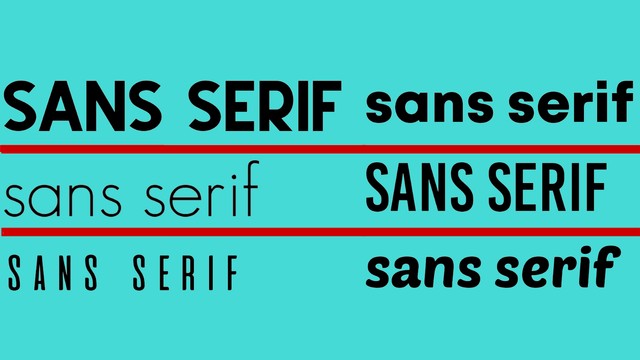
Sans Serif telah menjelma sebagai standar font dunia. Yang terbaru, Gojek mengubah font-nya menjadi Sans Serif. Menyusul Google, Spotify, Netflix, hingga Pinterest yang sudah lebih dulu menggunakan font tersebut.
Tentu bukan kebetulan jika merek dagang dunia itu hijrah ke Sans Serif. Bukan pula karena paksaan. Alasan yang paling masuk akal adalah, Sans Serif menawarkan cerita tentang kesederhanaan. Dan itu yang dibutuhkan orang saat ini.
Dalam sebuah riset berjudul ‘How Serif and Sans Serif Typefaces Influence Reading on Screen: An Eye Tracking Study’, disimpulkan bahwa pembaca, tentu kita sebagai konsumen, lebih cepat mencerna informasi saat dihadapkan dengan font Sans Serif.
Lebih dari itu, font Sans Serif jauh lebih efektif dalam mengajak pembaca untuk tetap fokus. Bahkan, pembaca dapat lebih mudah mendeteksi keberadaan kata-kata yang salah eja.
Dalam bahasa Perancis, ‘sans’ adalah ‘tanpa’. Sementara ‘Serif’ merujuk pada bagian yang berbentuk kait di ujung kaki. Sederhananya, Sans Serif adalah jenis huruf tanpa kait. Yang artinya, tak ada tangkai atau sirip di ujung kaki-kaki huruf.
Jika mengenal font seperti Times New Roman, Bodoni, atau Bookman Old Style, maka itu adalah jenis huruf bertangkai. Ilmu tipografi mengklasifikasikannya sebagai Serif. Sebuah font yang dahulu amat berjaya di era kerajaan Inggris.
Sebaliknya, Sans Serif jauh dari kata formal. Tak ada sirip dalam setiap hurufnya. Ia tampil mendobrak tradisi yang ada di Eropa kala itu. Dan karena itu, ia dianggap aneh di awal abad ke-19.
Sans Serif diciptakan oleh William Caslon IV pada tahun 1816. Caslon IV juga bukan orang sembarangan. Ia merupakan keturunan dari pencetus teks bahasa Inggris. Buyutnya, William Caslon I, adalah sosok pertama yang menetapkan gaya tipografi nasional bangsa Inggris.
Tak ada keterangan resmi mengapa Caslon IV mencetuskan Sans Serif. Sejumlah teori yang mengemuka adalah, Caslon IV sengaja memotong sirip di huruf karena permintaan klien. Tetapi, ada juga yang menyebut Caslon IV melakukannya sebatas percobaan.
Yang jelas, dari seluruh teori itu, Caslon IV tak terlalu berminat pada huruf yang ia ciptakan itu. Dalam What Are Grotesque Fonts? History, Inspiration and Examples, Harding menyebut Sans Serif sempat dilupakan. Masyarakat Eropa kala itu menyebutnya sebagai ‘Grotesque’. Font itu dianggap sangat jelek dan menjengkelkan.
Menariknya, meski sempat dicaci di abad ke-19, Sans Serif justru mulai berjaya di awal abad ke-20. Kala itu, modernitas tengah digugat. Romantissme terhadap era kejayaan masa lalu dianggap sebagai biang keladi atas terjadinya perang dunia.
Bertepatan dengan itu, gagasan menghidupkan kembali Sans Serif mengemuka. Alasan pragmatisnya, font Serif yang digunakan oleh para juru ketik melalui pena bulu dinilai sangat lambat. Ditambah lagi dengan goresan sirip yang hasilnya berbeda antara satu huruf dengan huruf lainnya.
Di Jerman, pada 1920-an, muncul sebuah gerakan Bauhaus. Gerakan tersebut berpangkal pada sebuah teori filsafat bernama utilitarianisme. Mereka percaya bahwa teks atau desain sekalipun harus menekankan asas kebermanfaatan.
Menurut gerakan Bauhaus, sesuatu dapat menjadi indah hanya kala melayani tujuan praktis. Konsekuensinya, upaya untuk menghiasi sebuah huruf dengan sirip adalah artifisial, sia-sia. Maka, font Sans Sarif adalah jawaban mereka.
Kini, Sans Sarif telah menjadi standar font dunia. Variannya pun makin banyak, misal Helvetica, Arial, Futura, Avant Garde, Bitstream Vera Sans, Century Gothic, serta banyak lainnya.
Meski begitu, situasi ini tak lepas dari kritik. Adalah Edmonson, seorang desainer asal Fransisco, AS, yang menyebut merek dagang yang menggunakan font tersebut salah kaprah.
“Tipografi ini ada di mana-mana, dan mereka melakukan pembenaran terhadap apa pun yang disajikan,” kata Edmonson dikutip dari Artsy.net
Edmonson adalah orang yang menyadari bahwa ada kesamaan jenis font yang digunakan oleh sejumlah merek dagang dunia. Untuk pertama kalinya, ia yang mengunggah kesamaan font di antara merek-merek itu di media sosial.
Sementara itu, Armin Vit, perancang grafis dan penulis blog branding populer Brand New, memandang bahwa dominasi Sans Serif adalah tren semata.
Ia mengatakan, jika ada sebuah perusahaan besar yang menggunakannya, maka perusahaan lain mengikuti. Terlepas dari fakta bahwa memang Sans Serif lebih mudah untuk dikenali.
"Mereka hanya menempuh rute yang sama, menghapus serif sial itu dengan imbalan kesederhanaan," timpal Vit.